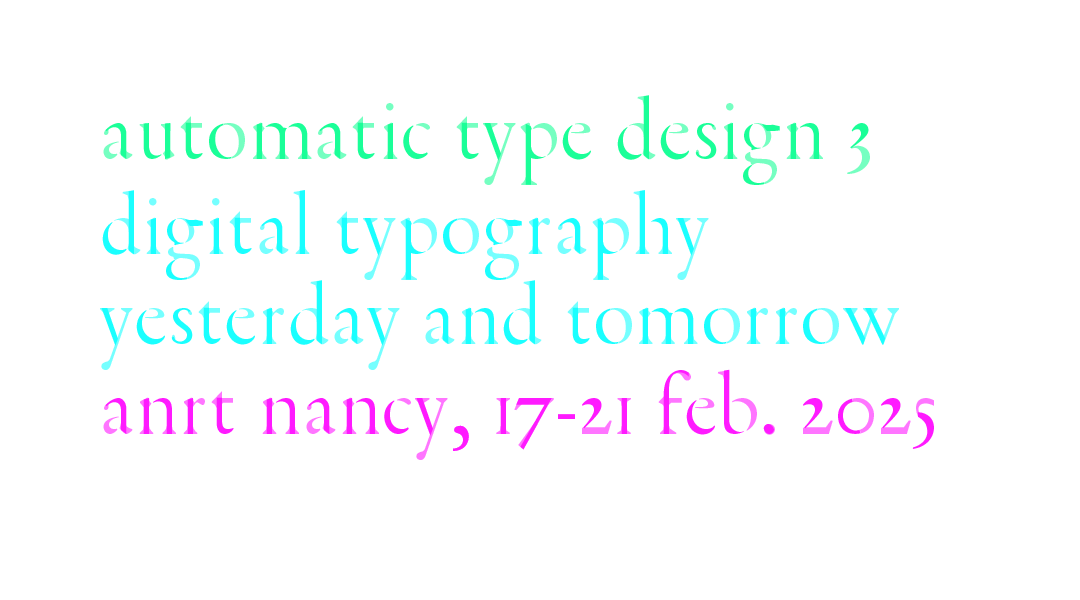
Bonjour, J’ai le plaisir de vous annoncer que la troisième édition du colloque international Automatic Type Design se déroulera à Nancy du 17 au 21 février 2025. Le thème est digital typography yesterday and tomorrow: l’objectif est à la fois de découvrir (et parfois ressusciter) des éditeurs de fontes historiques, tels que Ikarus, Fontographer, Metafont… et aussi d’explorer les outils de demain, en questionnant l’apport du deep learning et de l’IA dans le développement de fontes numériques. Les deux premiers jours seront consacrés à des workshops, et trois expositions seront présentées. Mais surtout, l’appel à communications est ouvert, sur la plateforme Easychair: https://easychair.org/cfp/ATD3 N’hésitez pas à proposer une conférence ou une démo, et à faire circuler l’information. Au plaisir de vous accueillir à Nancy, bien amicalement Thomas Huot-Marchand ![]() ______________________________________________________